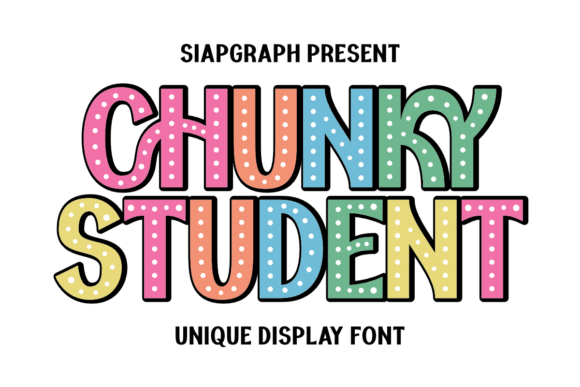
Chunky Student
適切なデザイン要素を見つけるのは難しい場合がありますが、Chunky Studentは作品を即座に引き立てる優れたコレクションを提供します。
POD(オンデマンド印刷)製品、結婚式の招待状、またはソーシャルメディアのグラフィックを作成している場合でも、Chunky Studentは理想的です。